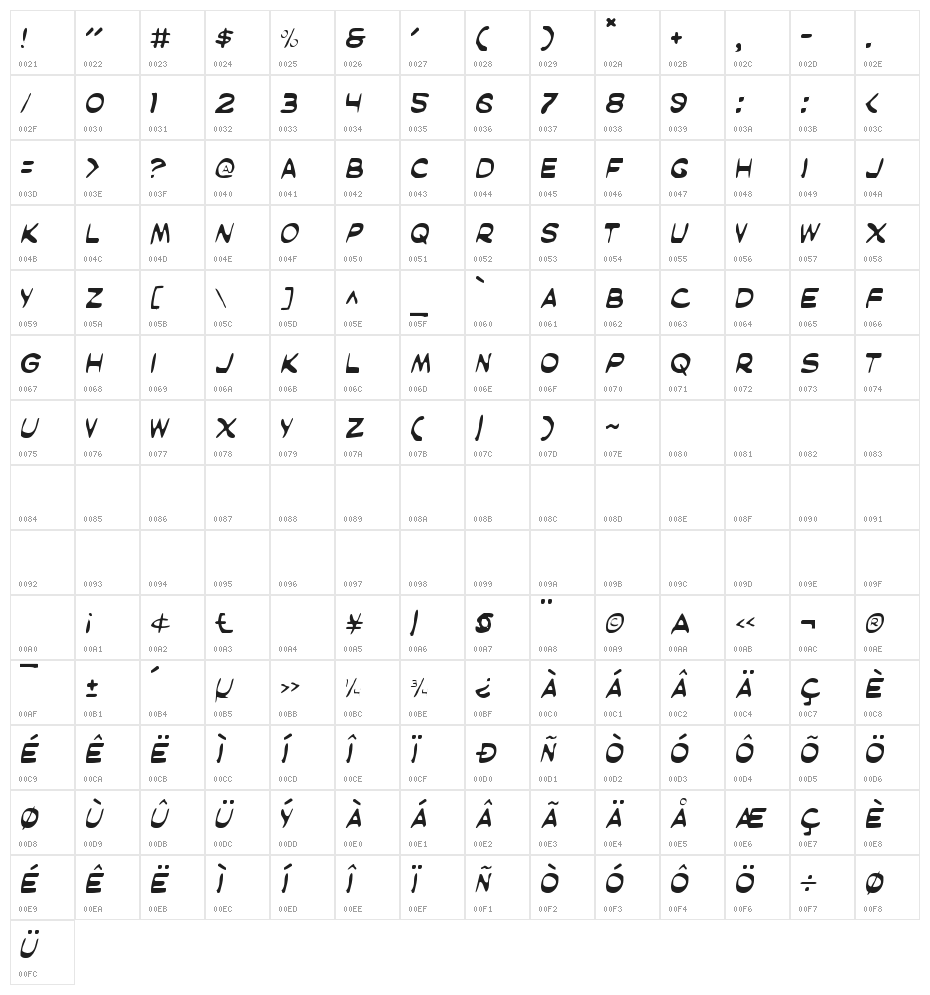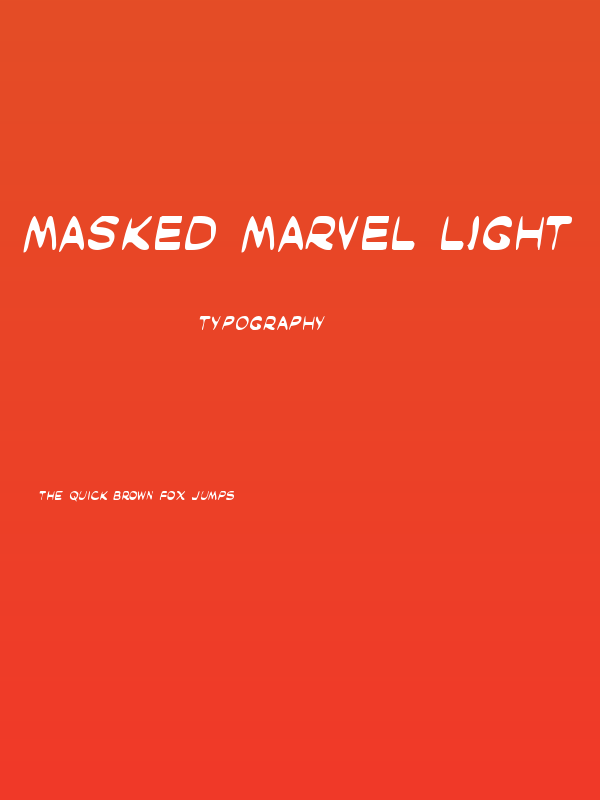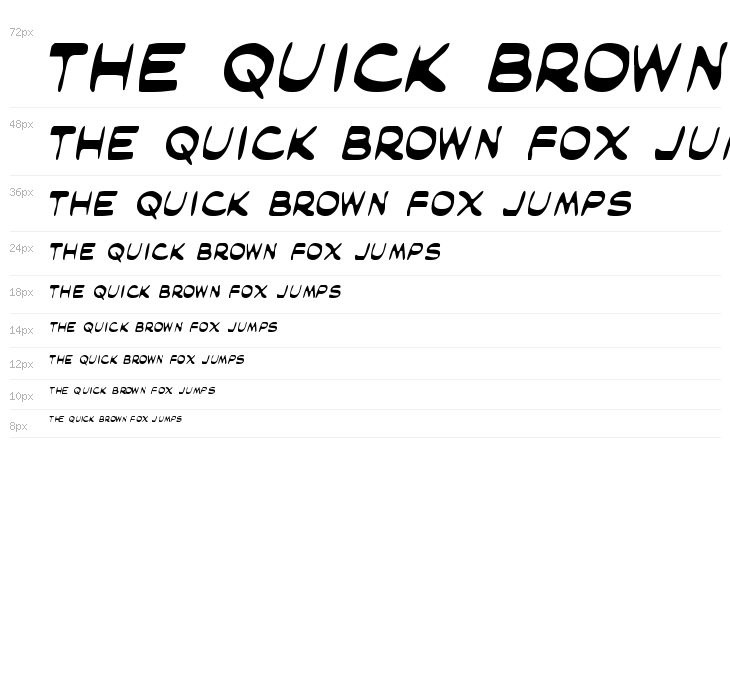
Masked Marvel Light Font
| Vorgeschlagene Projekte | Ideal for comic book titles, posters, branding, and any project needing a bold, energetic typeface. |